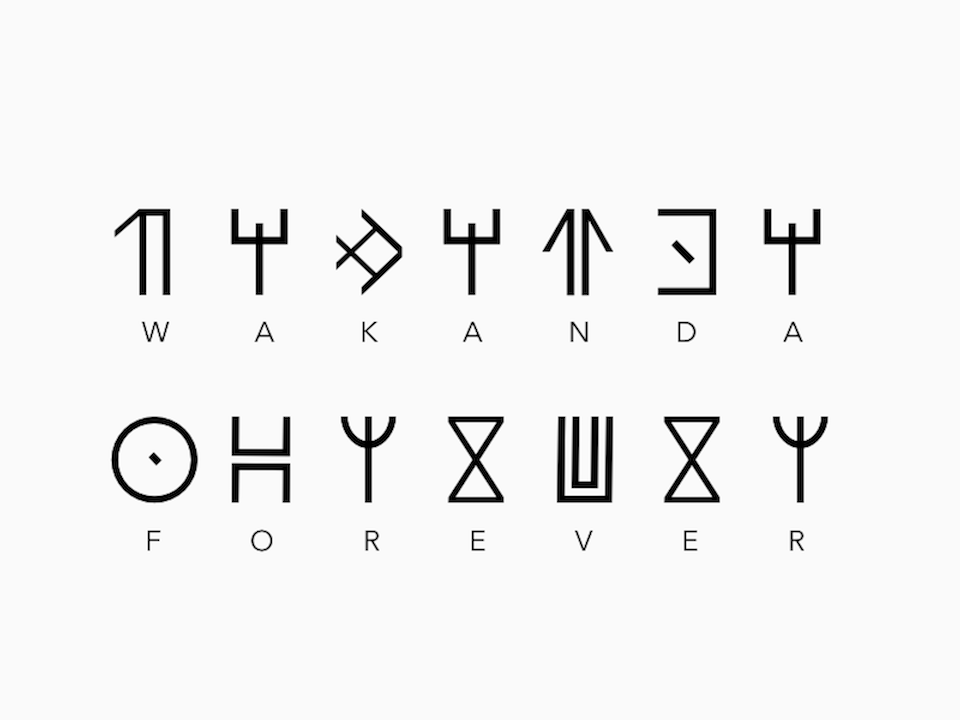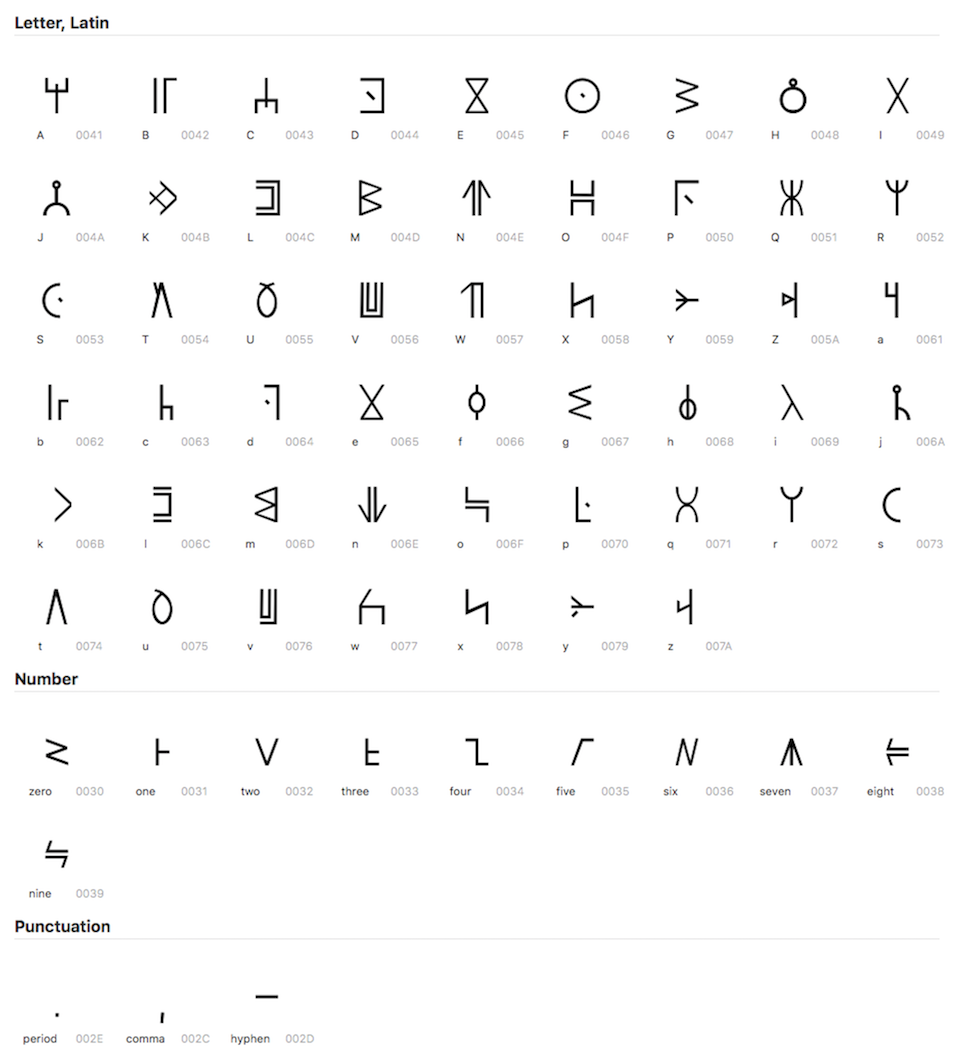
Mới đây nhà thiết kế có tên Adam Shady đã đăng tải lên mạng bộ font chữ Wakanda. Đây là font chữ được lấy cảm hứng từ vương quốc tưởng tượng Wakanda có trong bộ phim Black Panther. Bộ font Wakanda mà nhà thiết kế Adam Shady đăng tải bao gồm 2 phiên bản cho hệ điều hành Windows và macOS.
Bộ font chữ Wakanda lấy ý tưởng từ bộ phím Black Panther.
Font chữ Wakanda.
Hình ảnh về font chữ Wakanda.